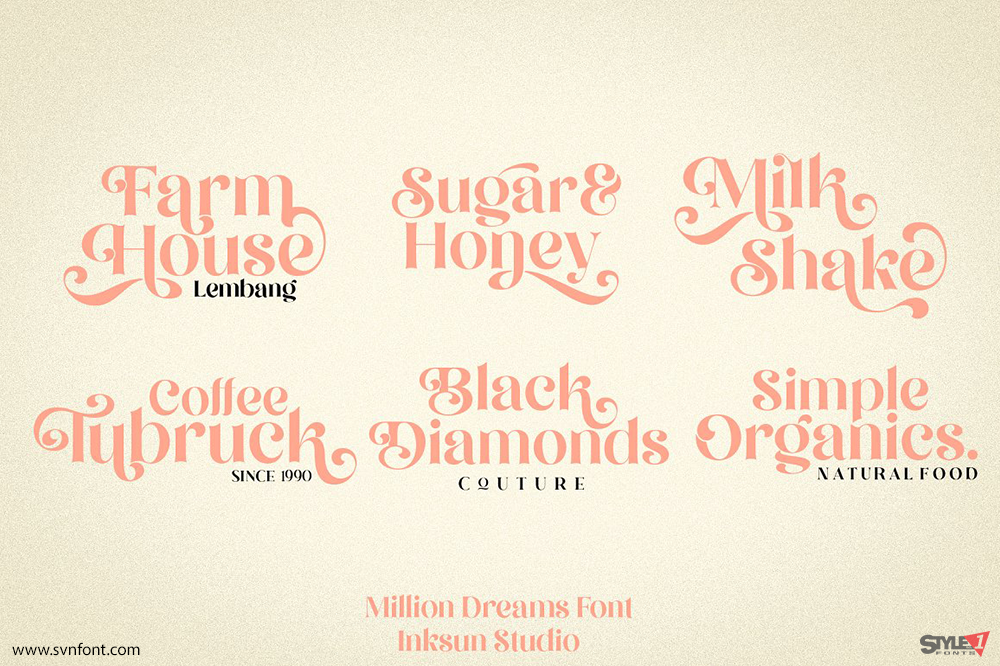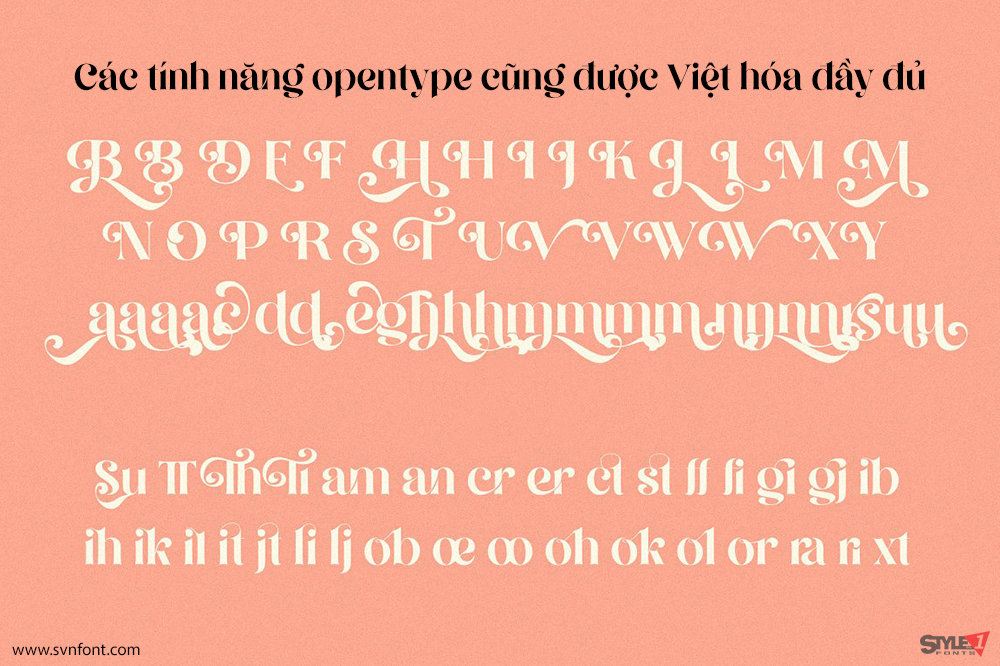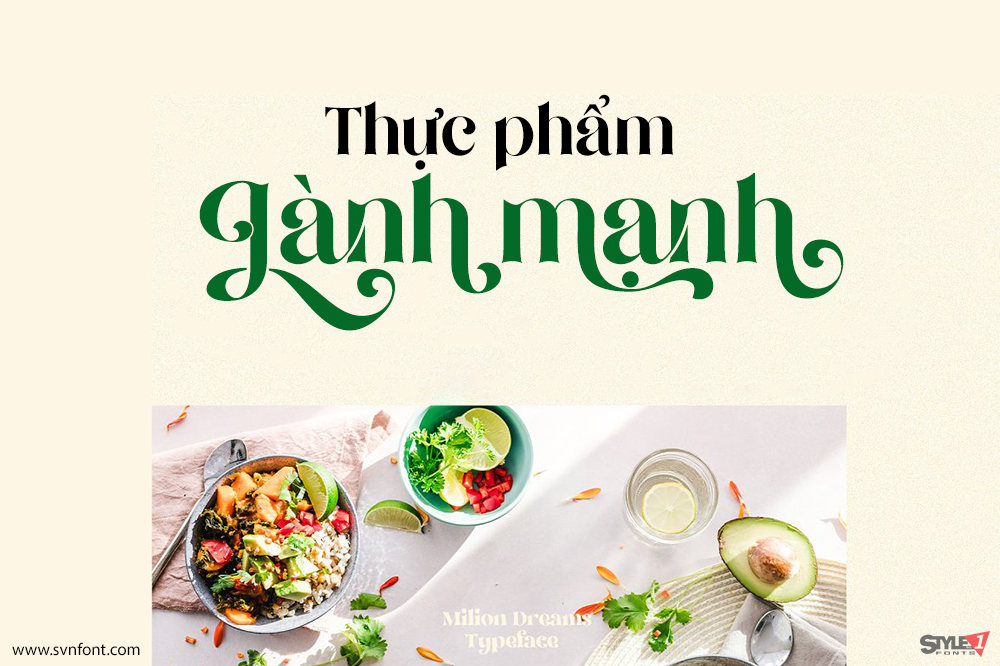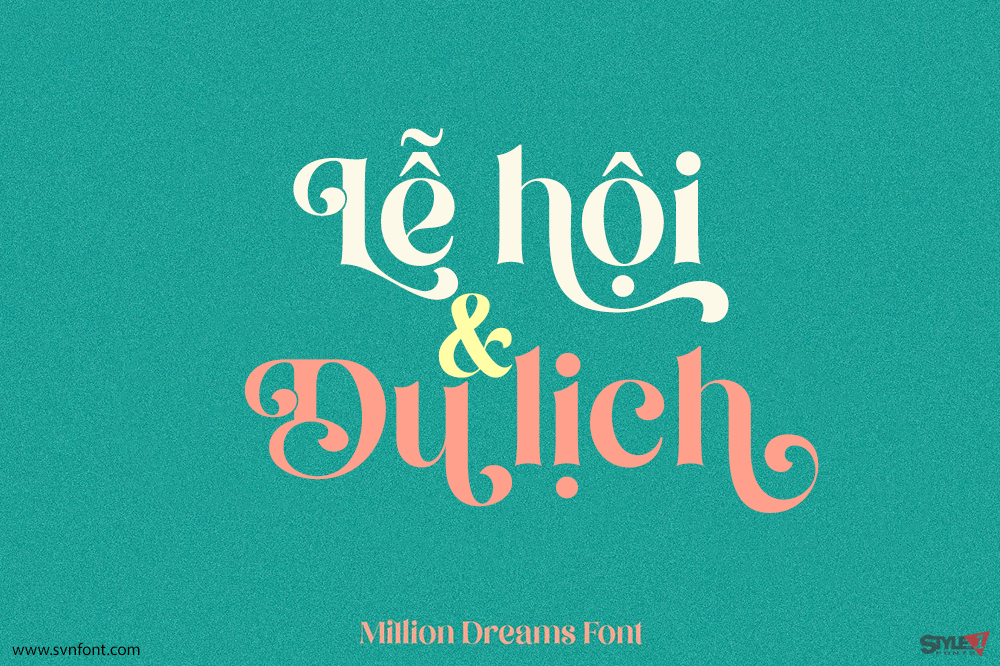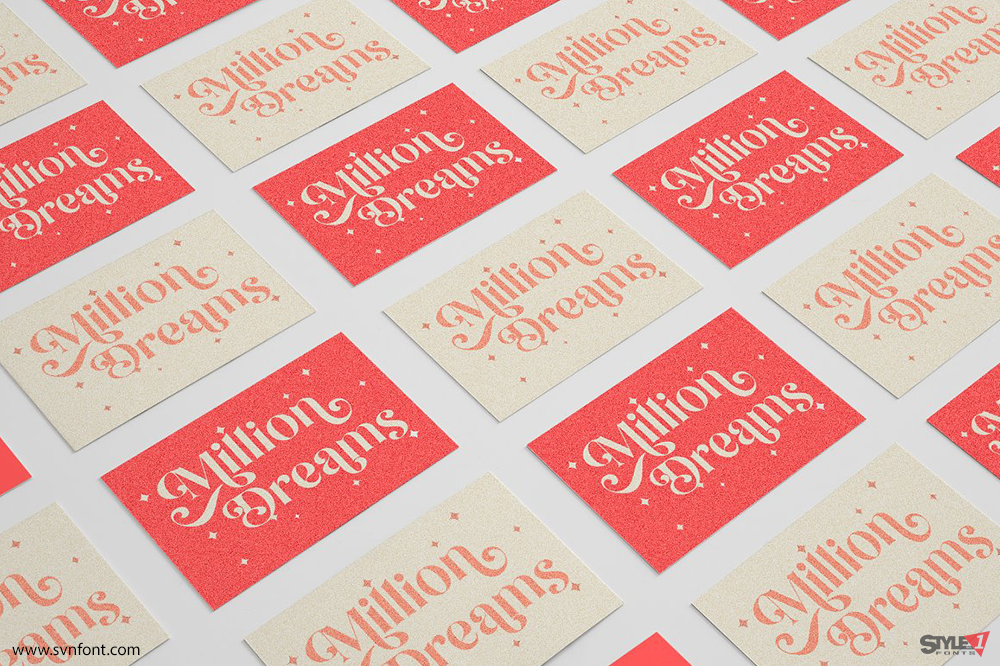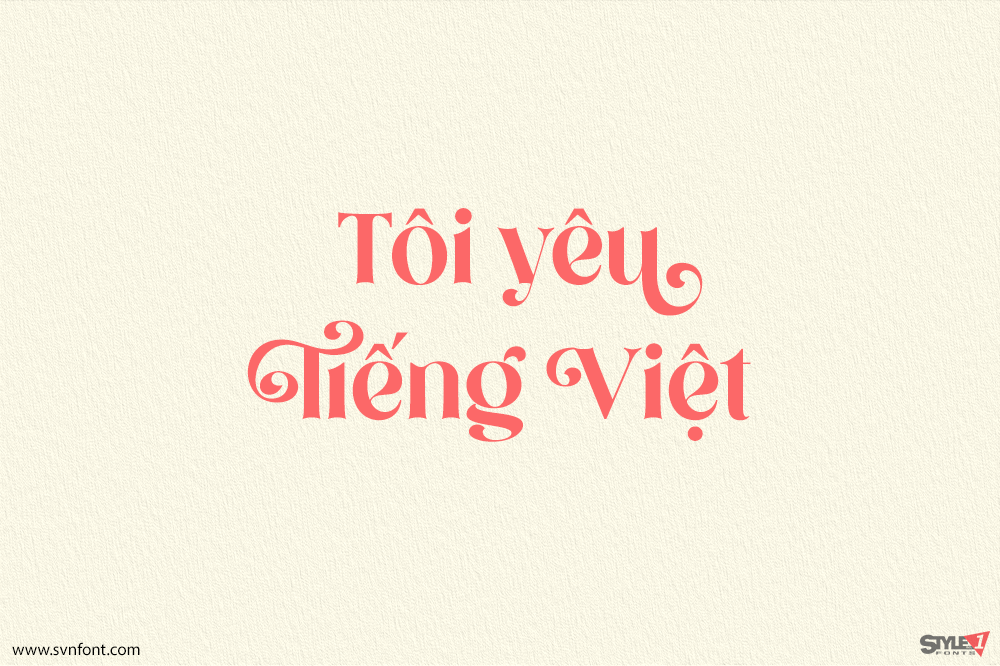
Xin chào mọi người, nhân dịp này chúng tôi xin giới thiệu Million Dreams, một trong những font chữ chủ lực mang phong cách vui nhộn, tuổi thơ, xinh xắn và nữ tính. Font được bổ sung stylistic và ligature tinh tế, rất phù hợp cho các dự án sáng tạo của bạn.
Nhà thiết kế: INKSUN
Nhà phát hành: INKSUN